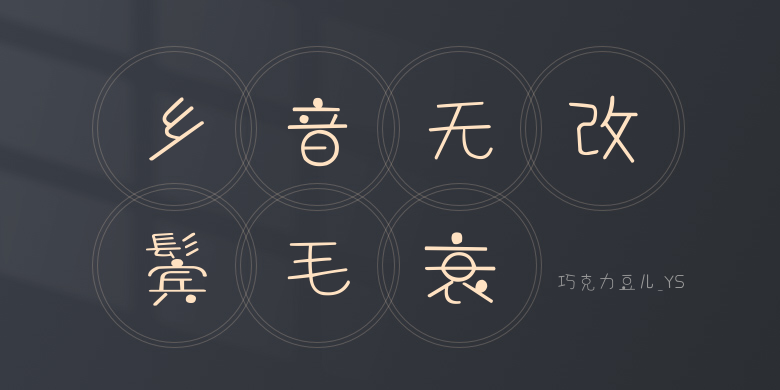
巧克力豆儿_YS
巧克力豆儿_YS,这款字体结构工整、笔画清晰,兼顾美观与易读性,适用于标题、正文、海报、包装、LOGO 等多种场景。字形优雅稳定,风格百搭耐看,适配日常排版与创意设计,让文字呈现更舒适、更具质感。巧克力豆儿_YS一笔一画,皆是细节,以均衡的比例、流畅的线条打造舒适视觉体验,字形端正大气,风格简约现代。无论是商业设计、品牌宣传还是日常排版,都能轻松驾驭,让文字更有格调与力量。巧克力豆儿_YS字体下载。